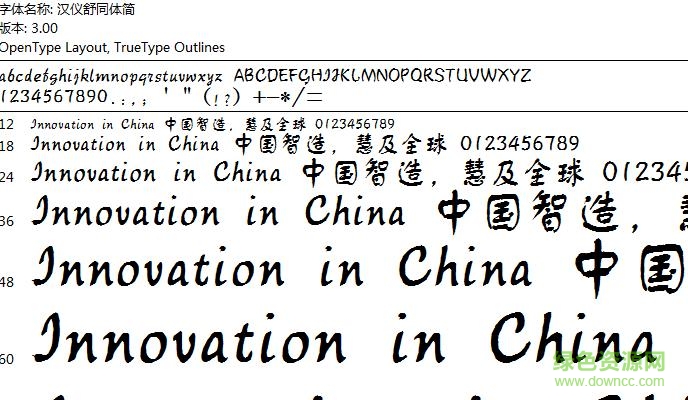
hyn1gj
hyn1gj字體是一款不可多得的書(shū)法字體,這款字體看上去氣勢(shì)磅礴,具有非常強(qiáng)烈的感染力,感興趣的朋友歡迎下載使用!
hyn1gj是什么字體?
hyn1gj即漢儀舒同體簡(jiǎn)體字體,是根據(jù)舒同先生的書(shū)法打造的一款特色中文字體,繼承了他書(shū)法寬博端莊,圓勁婉通,用筆老重,藏頭護(hù)尾,點(diǎn)劃潤(rùn)厚通暢的特色!